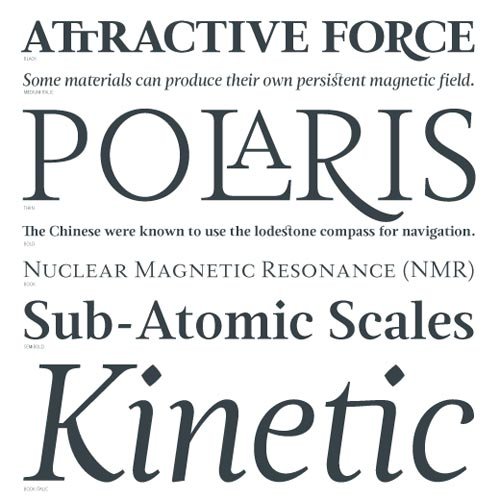
Als Neil Summerour, Professor für Graphic Design an der University of Georgia Lamar Dodd School of Art und einer der Geschäftsführer von Sliced Bread sowie Gründer des Fontlabels positype uns anschrieb, war eine deutliche Spur des Schreckens erkennbar. Er hat einen kürzlich entworfenen Font genau so benannt, wie wir unsere Magneta. Vielleicht lag dieses Missgeschick am Veröffentlichungsdatum (Freitag 13. Dezember 2009).
Die Magneta von Volcano-Type ist eine unserer ersten Schriften und wurde ca.1996 noch mit Ikarus digitalisiert. Damals war sie die Headline-Schrift für ein Fanatic-Plakat und stand ganz unter der DC-Ära: quick and dirty. Die MAGNETA von Summor ist dagegen ein ganz anderes Kaliber (erhältlich in Thin, Black Italic, Black, Bold Italic, Bold, SemiBold Italic, SemiBold, Medium Italic, Medium, Book Italic, Book, Thin Italic, Ornaments).
Die englische Beschreibung ist so elegant, dass es keinen Sinn macht, diese zu übersetzen:
To describe what inspired Magneta would be to add a little Dwiggins, throw in some Benton with a hint of Austin—wrap it up in a crisp, contemporary package and serve. The skeleton of the family is a Garalde (like my earlier Epic) but with a desire to produce something much more transitional and contemporary, I sought to simplify, simplify. Cap and ascenders share the same height, the x-height is slightly larger than expected which should make a functional typeface for editorial, headlines or where more visually complex systems are needed. The modulation is much more intentional than historical and creates some interesting interactions between the various weights. There are both Normal and Condensed widths available with 6 different weights and matching italics, small caps, oldstyle figures, swashes, stylistic and discretionary ligatures (that includes some fun majuscule ligatures in the roman styles), there is no lack of typographic goodness for the designer. To add some spice, a set of Decorative Ornaments have been created that include geometric, floral, curvilinear patterns and much more.
Wir sind ausnahmsweise einverstanden, dass es ab nun zwei Fonts mit gleichem Namen aber unterschiedlicher Herkunft, Qualität, Ausführung und Bestimmung gibt.